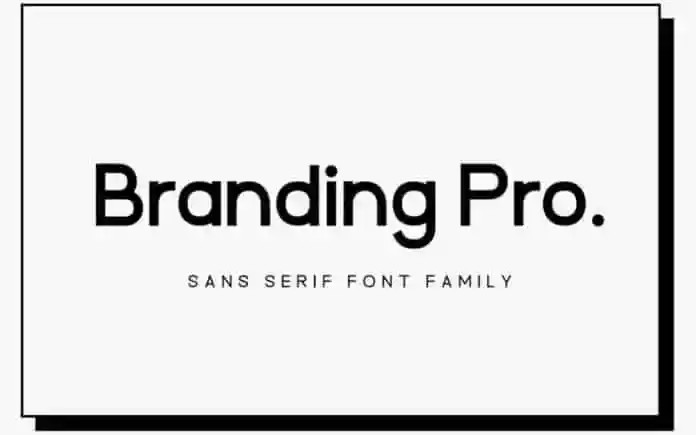
Branding Pro Sans Serif Font Family – Download Grátis
A ‘Branding Pro Sans Serif Font’ é uma família moderna de tipo sans-serif criada pelo designer Johandika Syahputra Lubis através do site 99designs. Esta família de tipos se destaca pela sua simplicidade e facilidade de combinação, permitindo que você personalize diversos projetos sem limitações. Seu design abrange uma ampla gama de estilos, desde conservadores até mais vibrantes e experimentais. As suas características modernas e elegantes permitem que você faça seus trabalhos se destacarem ainda mais. Este tipo é perfeito para um estilo retro, atemporal ou futurista, combinando com diversas idéias criativas. Experimente incorporá-la a seu próximo projeto de marca e observe como ela o impulsiona para cima!